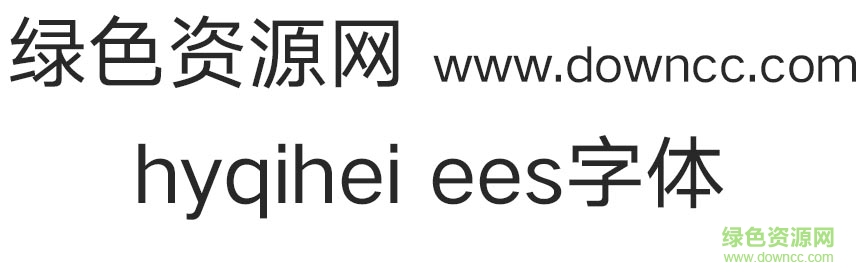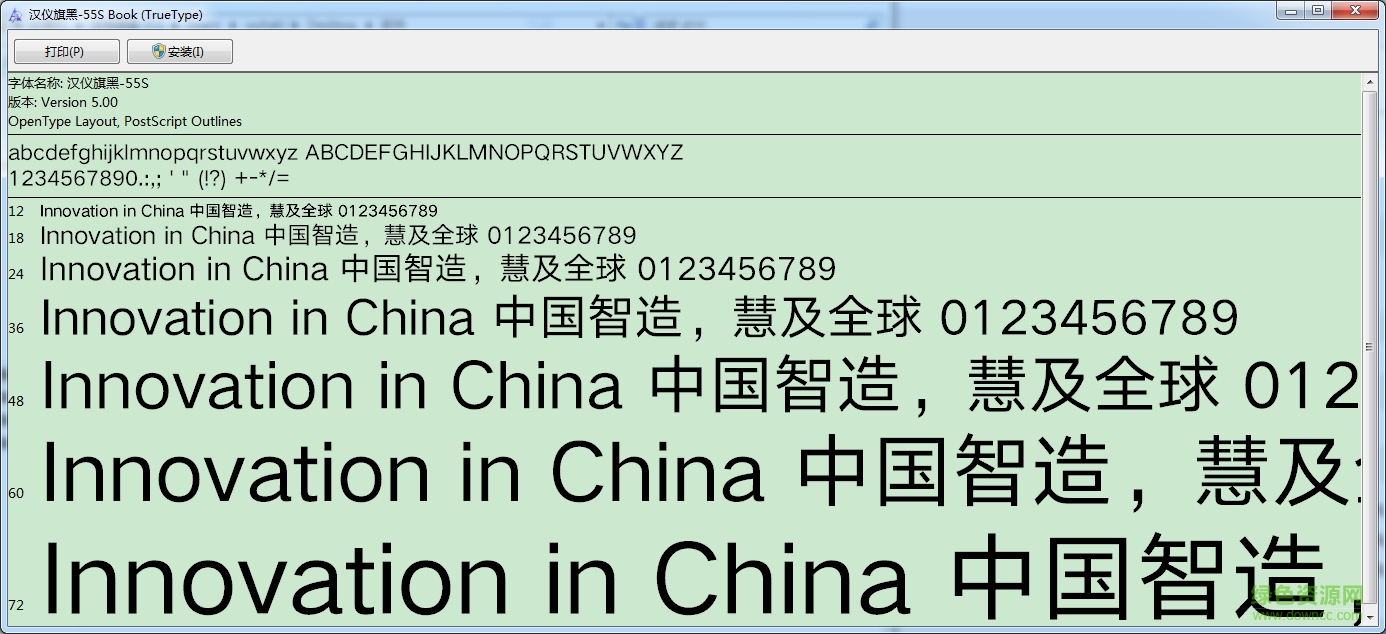
hyqihei ees字體是一款黑色文雅風(fēng)格字體軟件,木舟中黑體筆畫較粗黑,整體效果比較正規(guī),非常醒目,適用于廣告標(biāo)題的書寫,還有更多好看字體歡迎到綠色資源網(wǎng)下載使用!
hyqihei ees字體(漢儀旗黑-55S)是一款應(yīng)用于設(shè)計方面的黑體字體,該字體線條看起來比較的粗壯,字形端正大方得體,整體效果非常的出色,且字庫完整,可以廣泛應(yīng)用于廣告設(shè)計、宣傳海報、ppt、影視制作以及任何使用文字的領(lǐng)域。